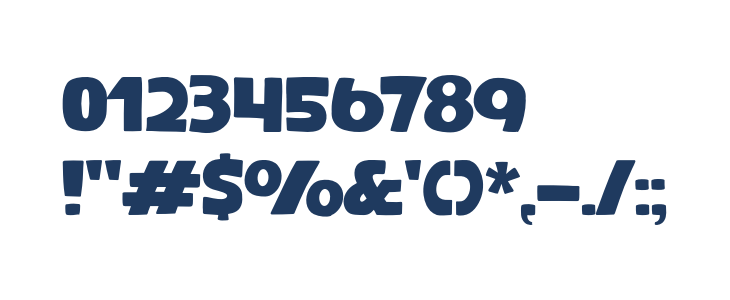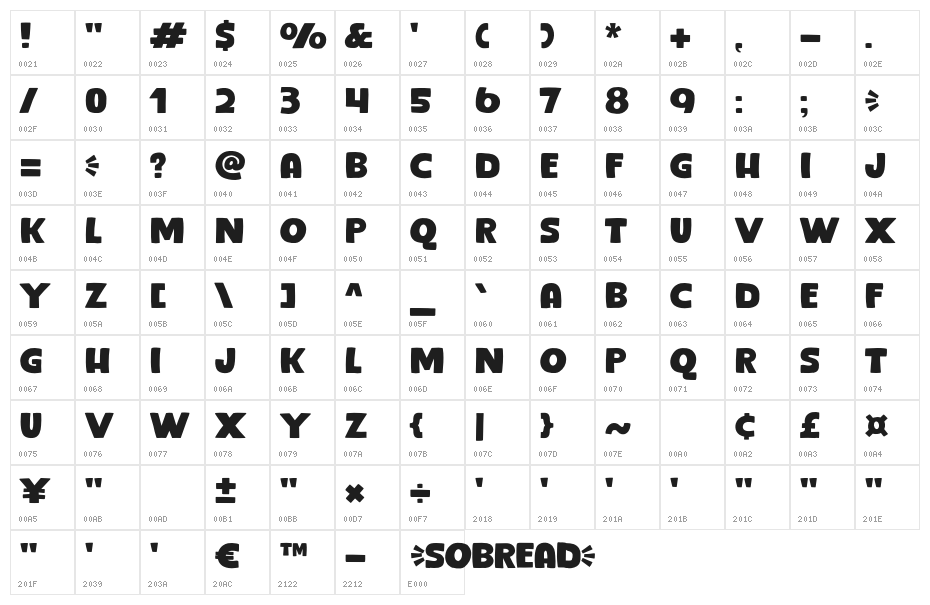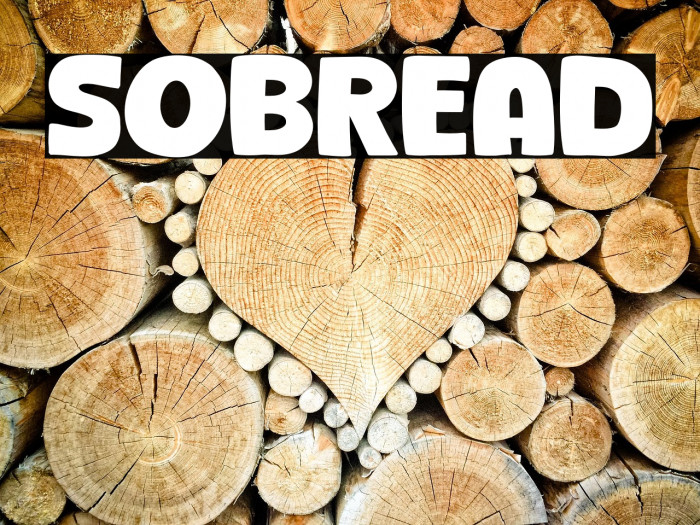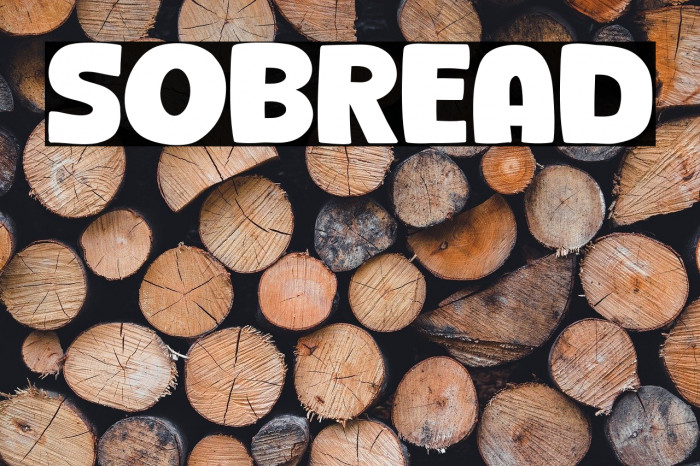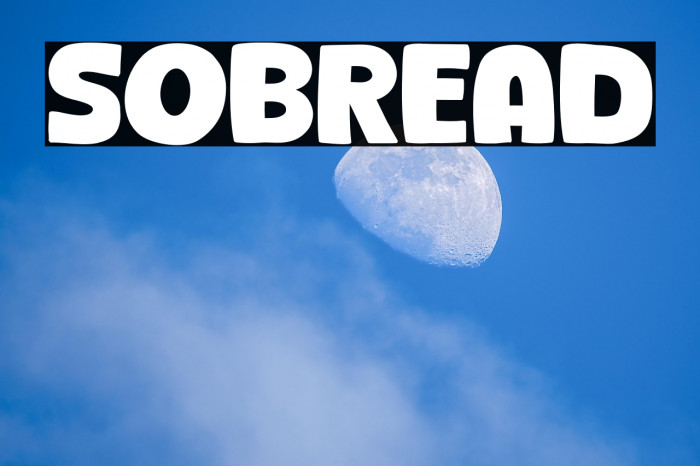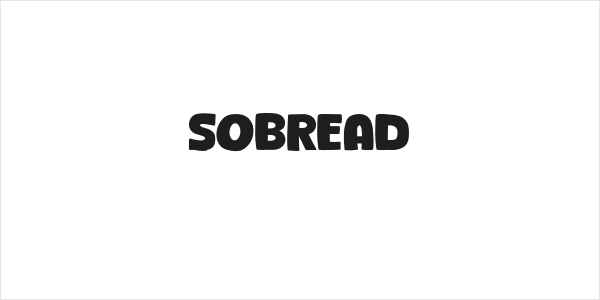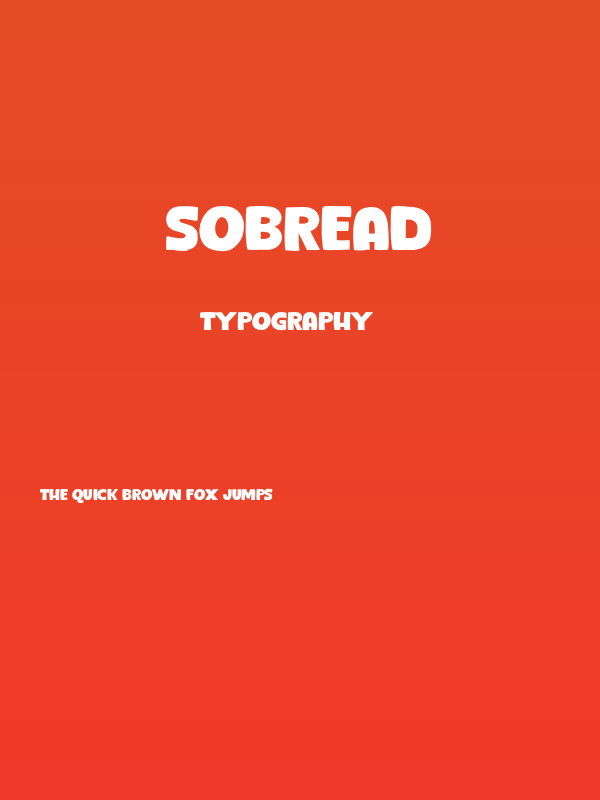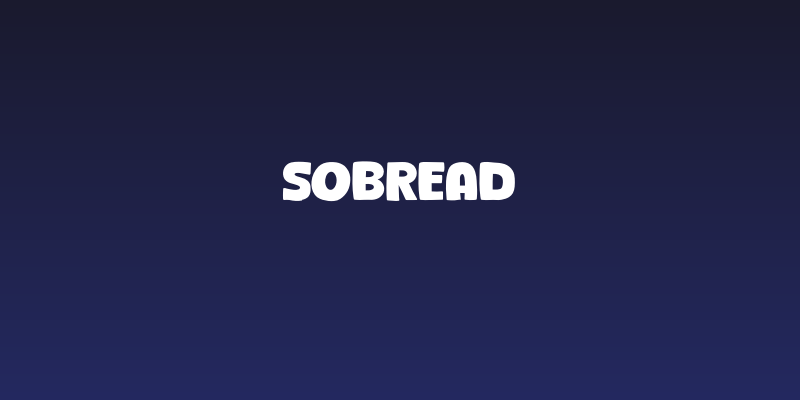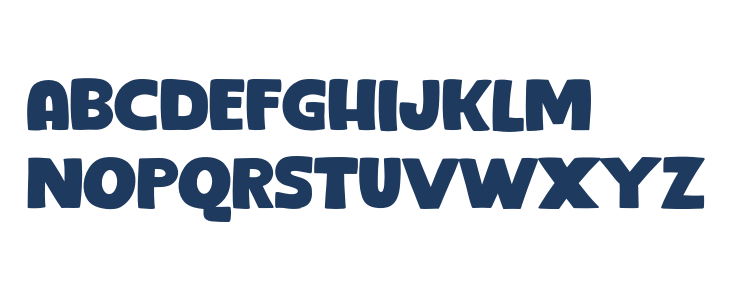
Sobread Font
| Gesamtstil | Playful, Friendly |
| Vorgeschlagene Projekte | Ideal for children's books, playful branding, posters, and social media graphics. |